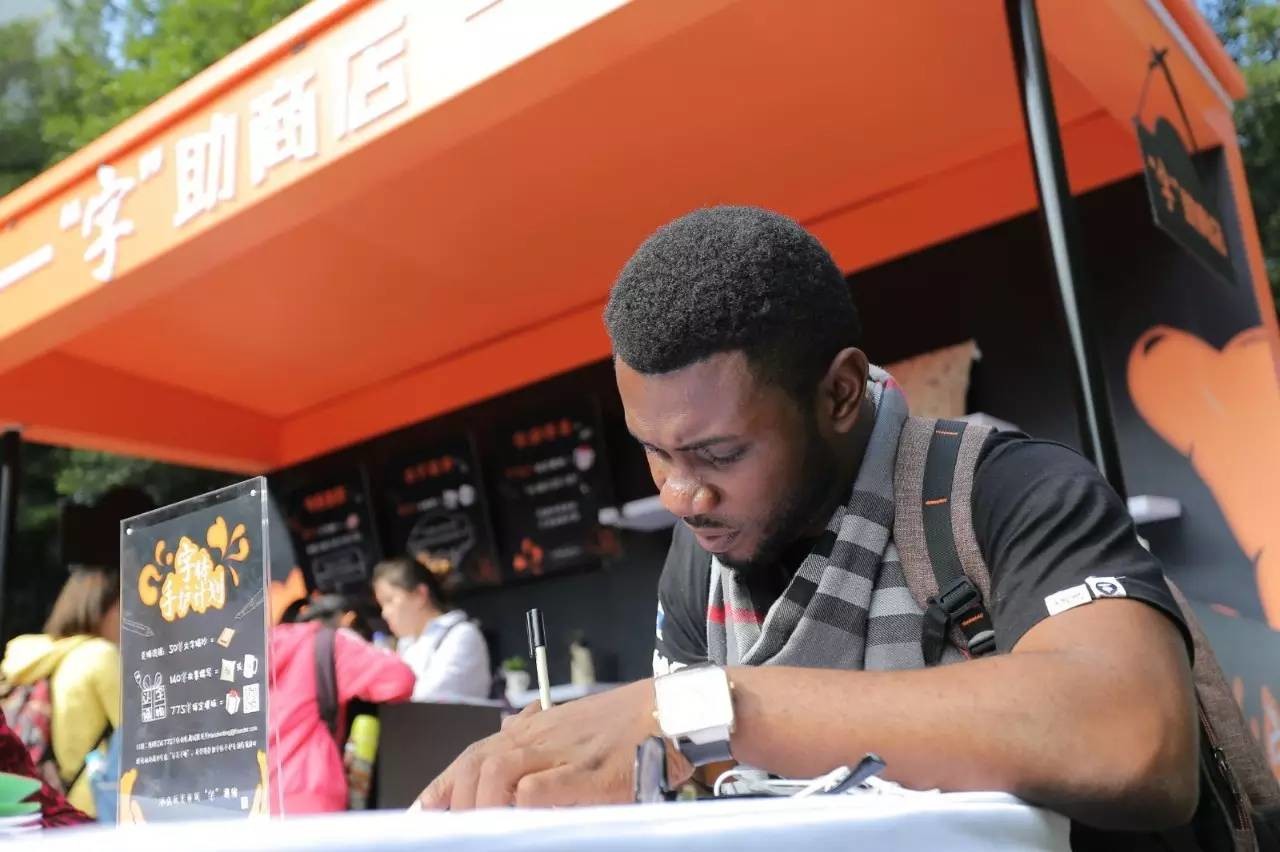
“字体手护计划”——让你重新爱上写字!
导语对于现今大学生而言,使用电脑、手机输入输出更像是他们日常进行文字沟通及表达的方式,一笔一划的写字应用机会在逐渐减少。然而,近日却出现了一家不收钱的商店,交易使用的“货币”正是大学生的手写字体!
近日,由方正手迹——“字体手护计划”发起的“字助商店”进驻南京、武汉、成都、广州33所大学的校园。学生只需现场手写汉字并提交字体作品,即可把手写字作为“货币”使造型独特用,交换个性趣味的物品。以物换物已是有趣,以字换物更具创意。“字助商店”让已然沦为“失写族”、“键盘侠”的大学生们不仅体验到“以字换物”的新奇,更是唤起大家对手写汉字的关注,提笔写字也是一件有价值的事。
这家造型独特的橙色商店坐落在大学校园,分外抢眼。店内错落有致摆放着个性的笔记本、帆布包、杯子和抱枕,店外座椅也摆满纸和笔,供“顾客”现场挥毫。学生们只需按要求现场提交手写字体作品,就可换取有汉字元素的抱枕、帆布袋、杯子、笔记本、雨伞等物品。以字换物——“字助商店”,用新颖创意的方式将手写字的价值展现在大学生面前。
字助商店为大学生带来一场用以字换物的崭新体验。脑洞大开的个性互动方式让字体也可以成为货币进行“交易”,展现手写汉字不一样的价值。正所谓字如其人,将个人化风格隐于字里行间,如流水般缓缓显现,让书写成为最有辨识度的个性标签。然而,科技在进步,电脑、手机一点一滴改变生活,年轻一族却因为科技遗失珍贵的文字精华。不做“失写族”,随手写字,让写字回归日常生活,重新唤起大学生对汉字文化的关注和支持,从自己做起,弘扬传统汉字文化。
据悉,别出心裁的“以字换物-创意字助商店”是方正手迹“字体手护计划”的首波活动,在四座城市的多所高校都受到了广大学生欢迎,在校内掀起手写汉字的热潮,截止上周现场关注人数将近10万。后续字体手护计划也将推出更丰富多彩的活动,面向全国大学生征集更多创意个性字体,以创新有趣的方式让写字这一传统汉字文化焕发新活力,让习惯做“键盘侠”的大学生们重新体验写字的价值与乐趣,爱上提笔写字。